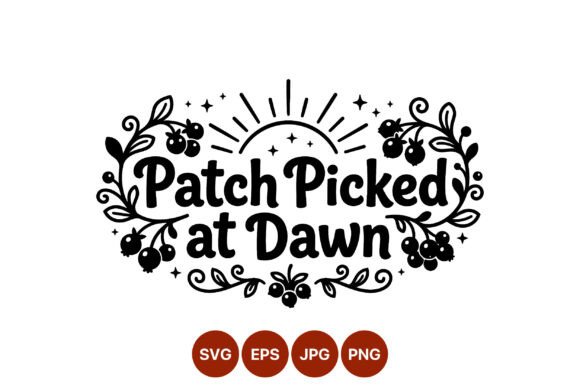
Patch Picked at Dawn Script Design
Als u op zoek bent naar hoogwaardige middelen zoals Patch Picked at Dawn Script Design, is dit premiumpakket een fantastische keuze voor uw creatieve projecten.
Met precisie gemaakt, biedt Patch Picked at Dawn Script Design strakke vectoren, vloeiende typografie en een commerciële licentie voor uw gemoedsrust.